実は簡単!WEBデザインのフォント選び
今日はデザイン制作に携わる人なら誰しもが常に考えている部分でもある字面。
意外にも用途によって最適なフォントは違っていて、それをなんとなくでも知っているだけで大きく間違えることはないのではないでしょうか。
もうフォントに迷わない!フォントの基本的な特徴をご紹介します。
フォントは大きく分けたら何種類?
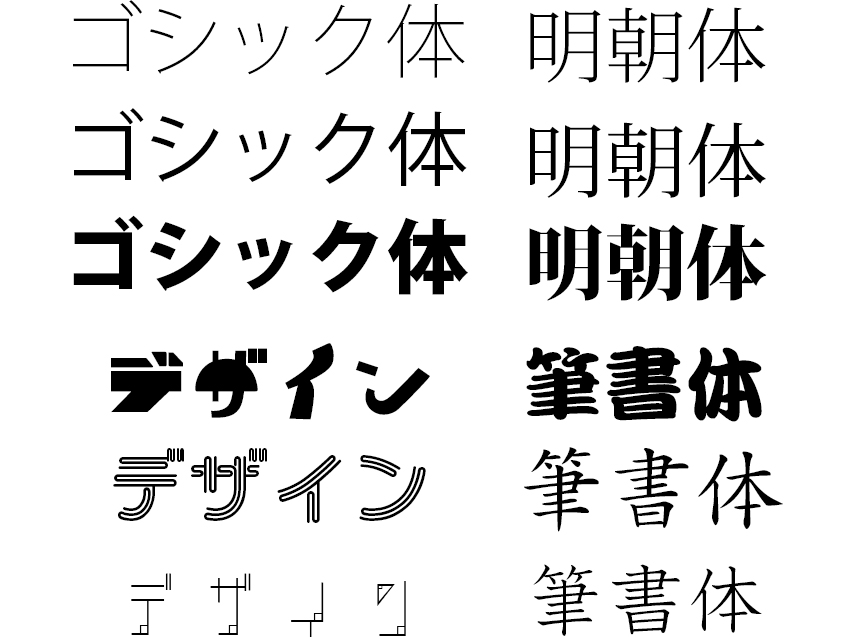
はい。
元も子もないこと言いますが、
世の中には無限にフォントがありますね。
その中でも分類は大きく4つに分けられます。
※あくまで僕がこの分け方をしているだけで「絶対にそう」という規定があるわけではないのでこの辺りは緩めにみてください。
代表的なものとしてまず、【ゴシック体】と【明朝体】の2つの分類があります。
そして、筆やペンで書いたような【筆書体】と独特な形でどれにも属しにくいものを【デザイン書体】に分けることができます。
僕の場合はこの4つから、ゴシック体、明朝体、その他を大まかにユーニークフォントとして分類し、デザインを考えています。
ただ、ユニークフォントでもゴシック、明朝の特徴を持っている場合はそれぞれに属した呼ばれ方もするため、かなり境界は曖昧だったりします。
ゴシック体の特徴
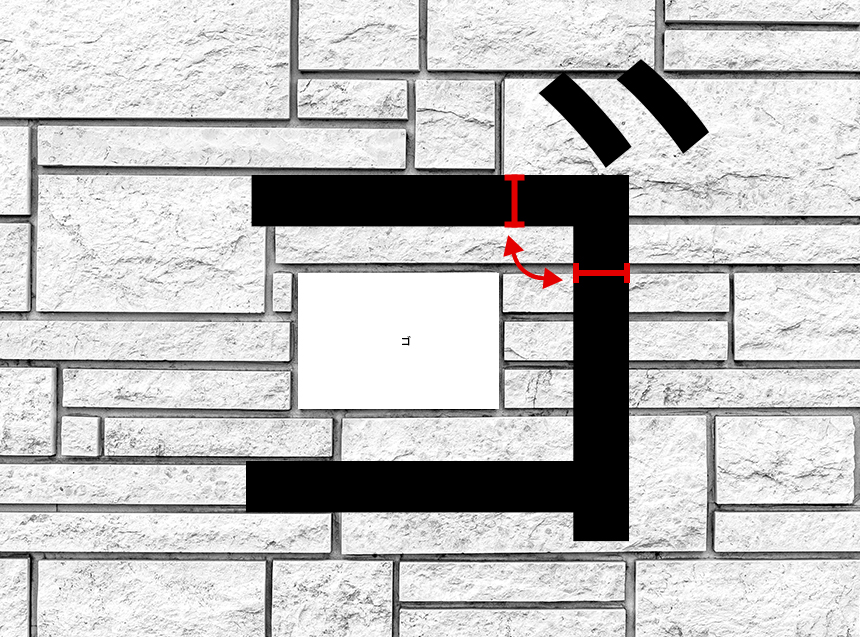
①シンプルで縮小しても読みやすい
全体的に太さが同じで装飾のないシンプルな書体で、明朝に比べて視認性が高く縮小しても読みやすい特徴を持っています。
シンプルなため、見かけることも多いスタンダードなフォントです。
②インパクトが出しやすい
シンプルながら縦横の線が均一なので、Bold以上の太いフォントを使うとインパクトがありタイトル・見出し・強調したい箇所に利用するのに向いています。
③WEBで使うならこっち
スマホやPCなどでは明朝体の場合、解像度の関係でぼやけて見える場合があるため、コンテンツの本文や説明文などの細かい文章などで圧倒的に利用されています。
そのためWEBサイトで多く目にするので親しみやすい文字となっています。
④どんなイメージを持たせるのか
角があり、硬く重厚なイメージをもつ書体のため「男性的」「モダン・現代的」「力強い」という様なイメージを与えます。
ビジネス系のサイトの他、細いフォントを使うことでスタイリッシュなサイトや未来的イメージのサイトにマッチします。
⑤デメリットもある
太さが均一で装飾がないので、字面がのっぺりとしてしまい、長文になると黒潰れしたように見えるという観点から敬遠されていました。
また、シンプルな分感情が伝わりにくいため、小説などには向いていないとされいます。
WEBサイトの場合、潰れにくいため長文の箇所でもゴシック体を使う場合が多いのですが、この場合、文字間隔や行間を広げてあげることでより読みやすくなります。
個人的には行間は一文字分くらい開けてあげること、太さはできるだけ細いものを選ぶことで黒塗りされたイメージを解消することができます。
明朝体の特徴
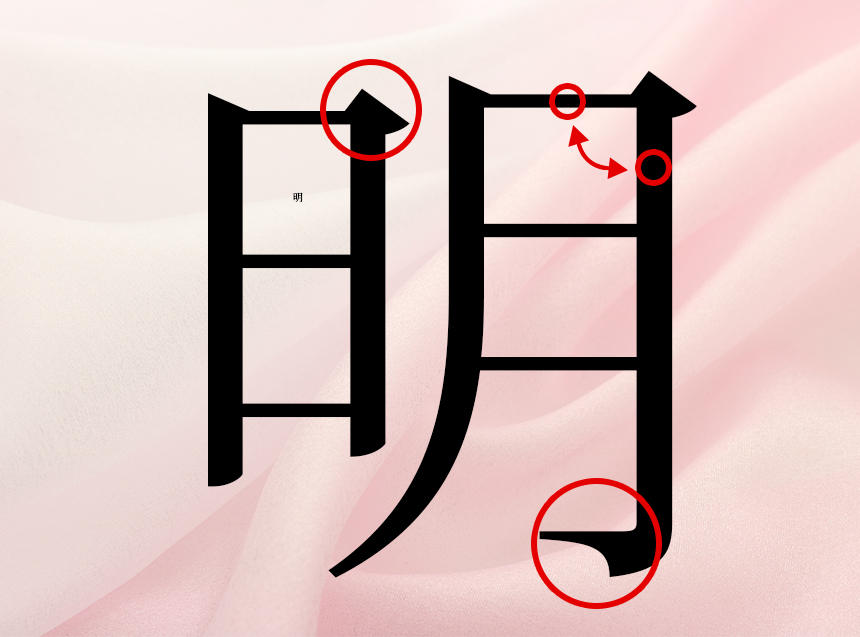
①筆で書いたような装飾のある書体
筆で書いたようにトメ・ハネがあり、線の太さは均衡ではなく、強弱があるのが特徴です。
ゴシック体ほどではありませんが、視認性が高く、線の太さに強弱があるので語彙が理解しやすいという利点があります。
②文字の判別がしやすい
横の線に対して縦の線が太く、ウロコなどの特徴がある書体あり、判別がしやすいのが特徴です。判別がしやすい分、読み続けたときに疲れにくいため長文に向いています。
③印刷物で使うならこっち
装飾があることで判別がしやすく、リズムもできるので読んでいても疲れにくく、飽きずらいため、教科書などを除き、新聞や書籍などDTPのほとんどで明朝体は使われています。
④どんなイメージを持たせるのか
線に強弱があり、優雅で落ち着いたイメージを持つ書体のため「女性的」「優雅・上品・高級感」「大人っぽい」という様なイメージを与えます。
WEBでは商品LPなど、緩急をつける場面でよく見られ、太さによって、インパクトや和風テイストなものから、補足することで繊細さを表現することもできます。
⑤デメリットもある
文字の判別がしやすく、長文向きではありますが、WEBページなど、解像度が低い媒体ではかえって文字がつぶれてしまい判別がしにくくなる場合があります。
そのため、長文での使用は印刷物が多く、WEBサイトで使用する場合はキャッチコピーや見出し部分に使うことでそのコンテンツの雰囲気やブランディング的な要素として使う場合が多いです。
また、この“判別しやすく可読性が高い”と言われている件ですが、実は条件があり、フォントの線が細い場合となります。
太くしてしまうとやはり文章が黒潰れしているように見えてしまいますね。
その他の書体
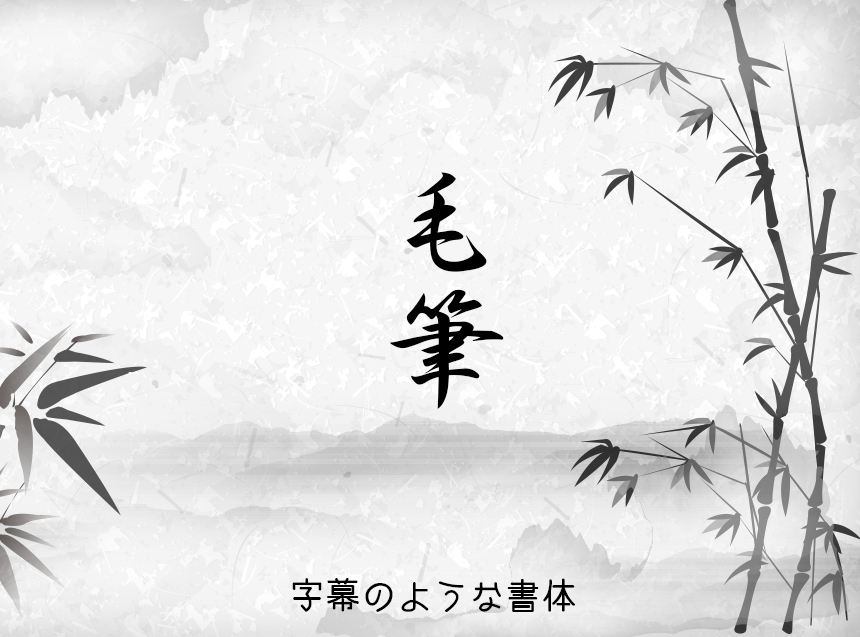
僕はひとまとめにユニークフォントと括ってしまっていますが、筆書体やデザイン書体はどうかというと、
基本的には「メインでは使わない」が結論です。
太いインパクトのある筆文字や特殊な装飾のついた文字は、印象だったり見栄えの部分ではアイキャッチとして効果的ですが、
「読ませる」という意図では単純に可読性が低いためオススメはできません(笑)
ただし、
こちらも広義に括ってしまっているので例えばそこまで可読性低くない書体ももちろんあり、サイトのブランデイングとしてマッチしていれば見出しなどには使用することもあります。
また、筆書体のくくりで教科書体がありますが、こちらは文字通り教科書に使われているフォントで、実際に普段描いているトメ、ハネに近い文字が特徴です。
手書きの雰囲気が強い筆書体の中では見やすくなじみがあり、長文にも使いやすい書体です。
このようにユニークフォントはあげればキリがないのですが、
簡単にまとめると、「装飾や個性が強いほど読みにくい!」と覚えてもらえれば良いかと思います。
まとめ
最後に簡単におさらいをすると、
WEBデザインの際に使うフォントの場合
・本文テキストに使用するなら細めのゴシック体が最も見やすい。
・見出しでインパクトを出すなら太めの書体(ゴシックでも明朝でも)
・キャッチコピーや見出しはターゲット層によって変わる
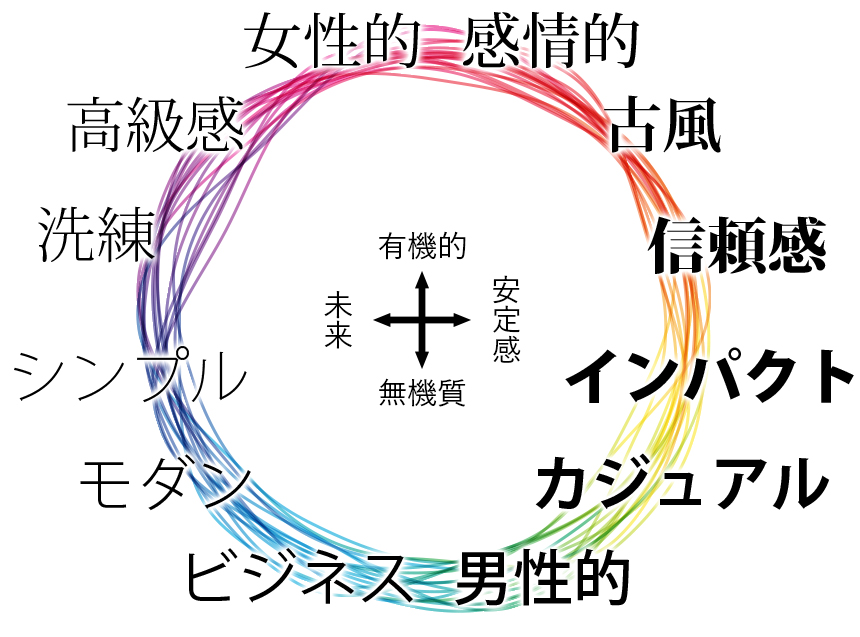
基本としてこちらの3点をベースにすれば数あるフォントから選ぶときの指標になるのではないでしょうか?
ちなみに最近の僕のブームは「游ゴシック体」です。
また、デザインの際はadobefontなどを参考にするとwebでも対応可能なフォントが使えます!